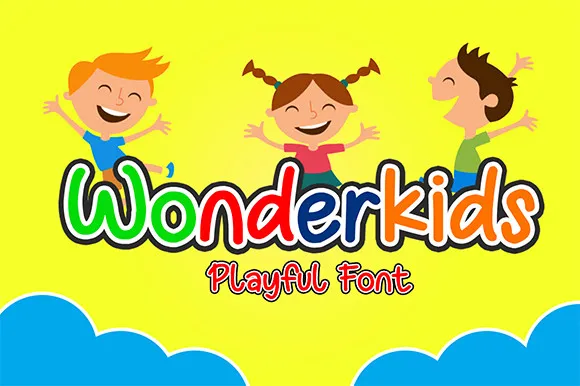
Wonderkids Display Font – Download Grátis
Descubra a nova adição à família de fontes Wonderkids Display Font criada pela BlueStyle. Esta fonte é uma delícia para os olhos e tem um tema infantil que promete encher suas criações de vida e diversão. Estamos falando de um tipo de exibição cheio de energia, ideal para aqueles momentos onde você quer dar uma pitada de personalidade a qualquer projeto design. Não importa o seu projeto — seja uma página de blog com imagens coloridas, sua próxima campanha publicitária ou até mesmo um site de criança: o Wonderkids Display Font irá adicionar um toque amigável e engraçado que tornará tudo mais encantador. Convidamos você a explorar esta nova fonte para dar vida ainda maior aos seus projetos!